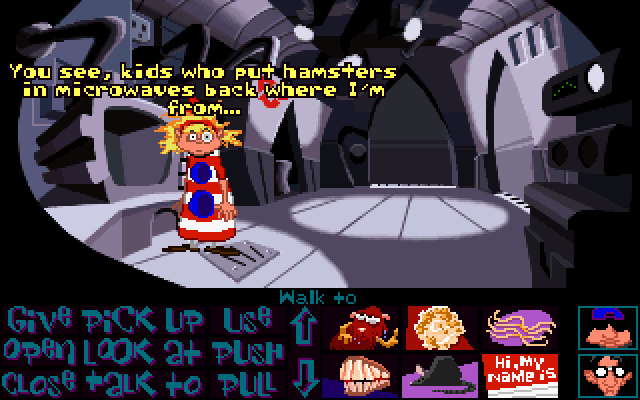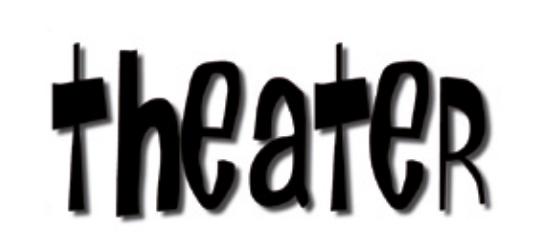
Handwritten? Brush?
Ich wäre sehr dankbar, wenn einer von euch Profis mir den Namen der abgebildeten Schrift nennen könnte.
Höchstwahrscheinlich ist diese normalerweise ohne Schlagschatten.